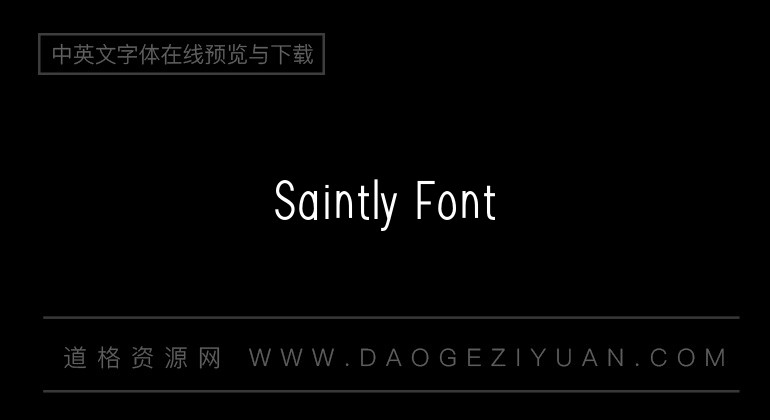
很抱歉,作为一名 AI 语言模型,我不具备视觉能力,无法提供字体的视觉效果。不过,我可以告诉你一些关于 Saintly Font 字体的一般信息。 Saintly Font 是一款免费的手写风格字体,由设计师 Alejo Bergmann 制作。这款字体具有一种自然、冷静和圣洁的感觉,适用于多种情境,如婚礼、宗教、精神和社交场合等。字体具有不同的字形、大小和样式,可用于设计包装、海报、贺卡、书籍封面等等。 如果你需要查看字体的外观和样式,可以在搜索引擎上输入“Saintly Font”来查看。希望我的回答对你有所帮助!内容介绍
Saintly Font是一款非常不错的手写艺术字体,具有很好的视觉感,适合于文化类的宣传设计、商业类品牌的广告和产品包装设计以及个性化文字排版等较多场景。